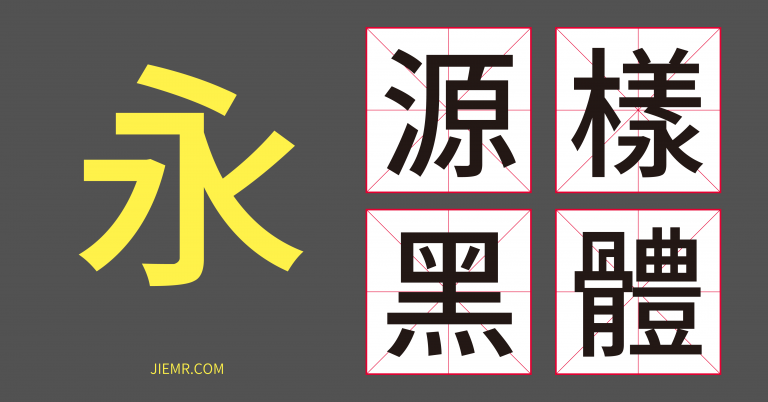
免費繁體中文字型:源樣黑體,可用於商業用途使用 由 李介介 · 已發表 2017-10-23 · 已更新 2018-01-14 這款字體是承襲思源黑體原有的特色,思源黑體除了支援多種語言外,更棒的是採開放原始碼,讓字體開發者可以依據它來進行修改,創造出更多、更不一樣的特色字型,這款源樣黑體是出自 But,就是從思源黑體修改而來,在格式上轉換為 TrueType(TTF)版,也在細部上做了些許的調整和變化,使它看起來更為銳利 比起 Windows 內建的微軟正黑體只有粗體與正常的粗細變化,這款「源樣黑體」就有七種粗細的變化,在設計排版上會更加靈活與方便,下載的路徑請點下方 由 github 下載或由介介的備用位置下載 分享給朋友FacebookTwitterTelegram更多LinkedInTumblrWhatsApp電子郵件PocketSkype